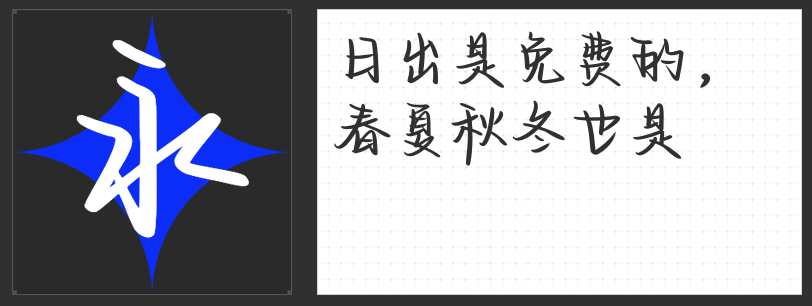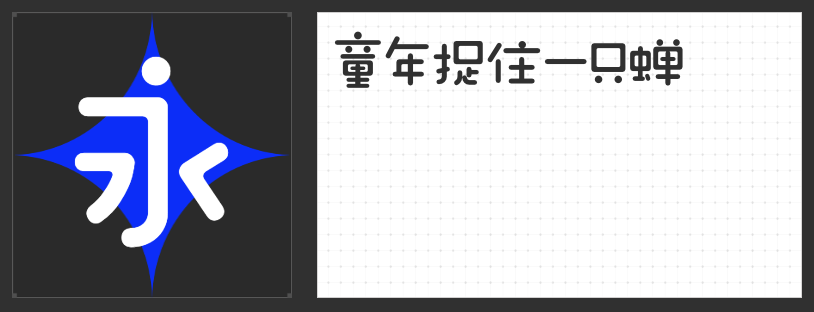
影视剪辑新风尚:精选字体推荐,让每一帧画面跃动创意火花
在同人向影视剪辑视频中,文字不仅是传递信息的载体,更是视觉艺术的重要组成部分。选择恰当的字体,能够瞬间提升视频的氛围感与观赏体验,让故事更加引人入胜。以下是几款推荐用于影视剪辑视频的字体风格,它们各具特色,适用于不同场景。
1.高手字斋东京体
对于怀旧向的同人剪辑,情怀复古体是不可或缺的选择。高手字斋东京体模仿了旧时代的印刷风格,带有岁月的痕迹,能够迅速营造出一种温馨而怀旧的氛围,让观众仿佛穿越时空,与原作角色再次相遇。
为了满足现代观众的审美需求,设计将传统毛笔书法与现代设计元素相结合,创造出融合创新体的毛笔字体。造字侠醉春风简繁 苍劲既保留了毛笔书法的韵味,又融入了现代设计的时尚感。
手写体以其独特的韵味和个性,成为同人创作中的宠儿。也字工厂电影旁白体笔触细腻温婉,能够精准传达角色的情感与性格,为剪辑视频增添一抹不可复制的魅力。在同人剪辑中,手写体常被用于字幕、标题或注释,让作品更加贴近原作风格。
可爱字体如同甜蜜的糖果,为作品增添无限趣味与萌感。励字造桃气圆 常规不仅适合表现角色间的温馨日常,还能为搞笑、轻松的同人剧情增添更多笑点。
在选择字体时,需要考虑其与作品主题、风格及情感基调的契合度。同时,保持字体的清晰可读性与视觉协调性也是至关重要的。通过精心挑选与搭配字体,您的影视剪辑视频将更加生动有趣,为观众带来一场视觉与情感的双重盛宴。